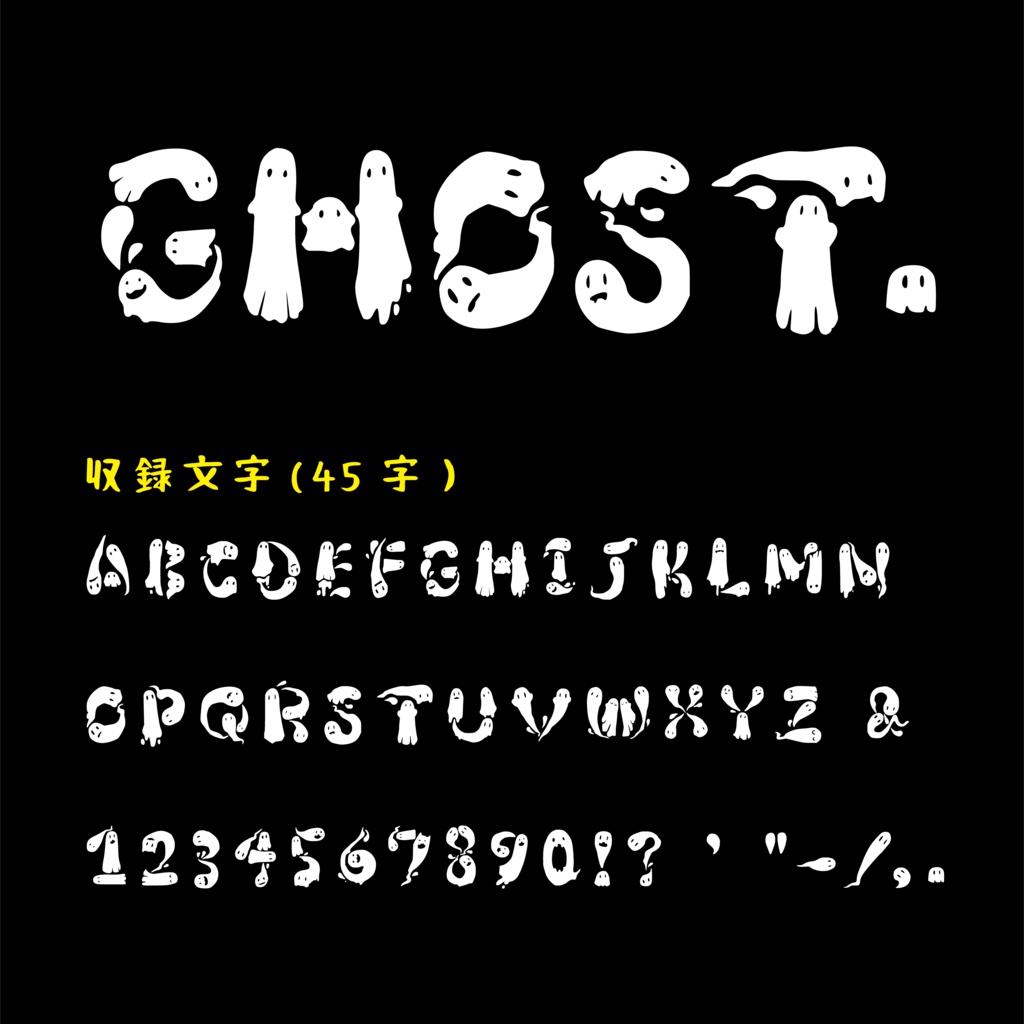
ハロウィンっぽいデザインを作りたい時にちょっと便利かも!と思って作りました。おばけがモチーフの英語フォントです。
初めて作ったフォントなので種類は少なめですがアルファベット(大文字)と数字は問題なく打てます。
収録文字(45文字!本当に最低限しか作ってない…!)
ABCDEFGHIJKLMNOPQRSTUVWXYZ1234567890-,.'"!?&/